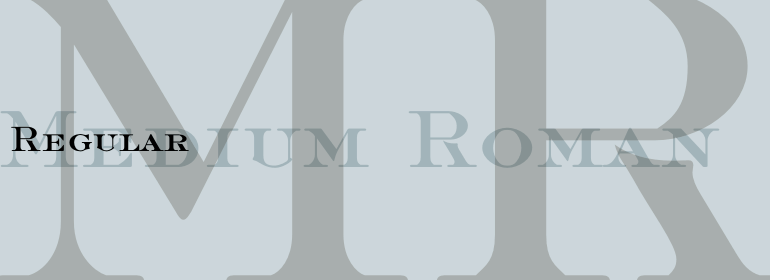
Medium™ Roman
Medium™ Roman,这款字体结构工整、笔画清晰,兼顾美观与易读性,适用于标题、正文、海报、包装、LOGO 等多种场景。字形优雅稳定,风格百搭耐看,适配日常排版与创意设计,让文字呈现更舒适、更具质感。Medium™ Roman一笔一画,皆是细节,以均衡的比例、流畅的线条打造舒适视觉体验,字形端正大气,风格简约现代。无论是商业设计、品牌宣传还是日常排版,都能轻松驾驭,让文字更有格调与力量。Medium™ Roman字体下载。
Medium Roman is an engravers, all-capitals font for invitations and stationery. Particular characteristics of the Medium Roman font are the tail on Q and the spurs on J and U.